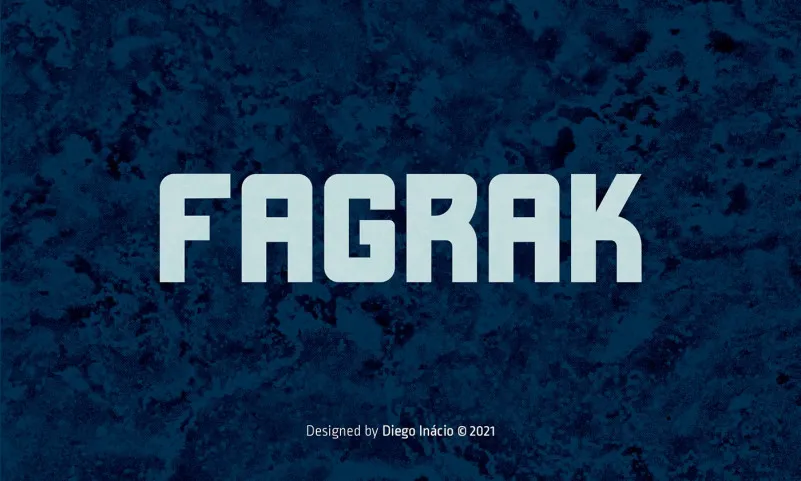
Fagrak Font – Fonte Grátis
Fagrak Font
A Fagrak Font é uma tipografia sans-serif geometrica que oferece uma aparição moderna com um olhar futurista. Sua aparência retangular e monolinada traz a sensação de digital retro, tornando-a perfeita para uso em logotipos, posters e publicações nas redes sociais. O design retro-digital da Fagrak Font combina de forma elegante e criativa, permitindo que você combine caracteres para criar seus próprios estilos únicos. Este tipo de letra foi projetada para ser fácil de ler e extremamente versátil, tornando-a uma excelente escolha para qualquer aplicação visual em sua marca ou projeto de design. A Fagrak Font é o ideal para dar um toque único a seu próximo projeto visual, se você busca uma tipografia moderna com um sabor nostálgico digital.